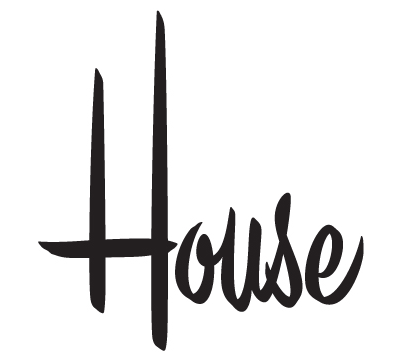
House Industries
• Land: Vereinigte Staaten
• Ort: Yorklyn, Delaware
• Gegründet: 1990
House Industries ist ein in Yorklyn (Delaware) ansässiger Schriftanbieter, der 1990 von Andy Cruz and Rich Roat gegründet wurde. Die Schriften haben in der Regel starke Bezüge zur amerikanischen Design-Geschichte und zum Designhandwerk, wie es etwa von Schildermalern ausgeübt wurde.
Bekannt sind House Industries auch für ihr Marketing. Zu den Schriften gibt es thematisch passende Accessoires, die von Kissen bis zu kompletten Möbeln reichen können.